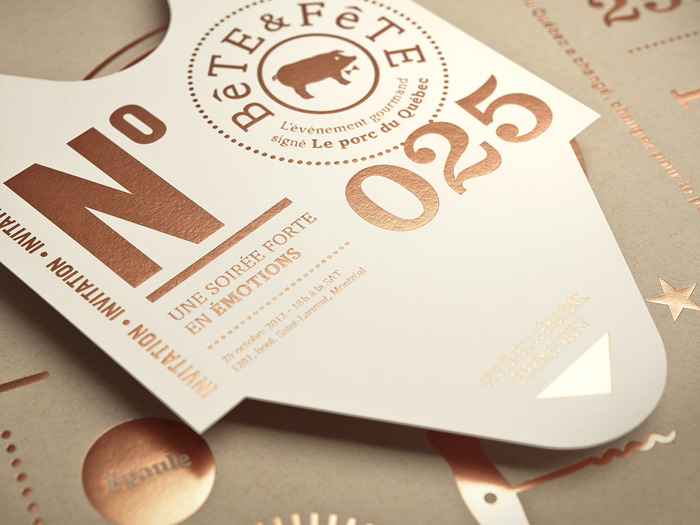
Schriftempfehlung
Da ich leider nicht vom Fach bind brauche ich einmal Rat von jemandem der
sich mit so etwas auskennt - nämlich von Euch.
Ich habe für meine Firma (Buchbinderei) ein Logo entworfen was genau meinen Vorstellungen
entspricht. Zu einem Logo gehören natürlich auch Briefbogen Visitenkarten etc.. Für diese benötige
ich unbedingt eine Schriftempfehlung, habe schon super viele ausprobiert aber so richtig stimmig
waren keine - ich hoffe auf Eure Unterstützung!!1
Ich habe den Eindruck Aria bzw. Aria Text könnte gut passen.
Aber auch eine »fließende« Sans wie Mr Eves halte ich für formal adäquat.
Zu Deinem Logoentwurf könnten eine ganze Reihe von Schriften passen, sowohl Serifenschriften als auch Serifenlose. Das hängt so ein bisschen davon ab, wie Du Deine Buchbinderei positionieren möchtest. Eher traditionell ausgerichtet könnte eine klassisch anmutende Antiqua wie die Mercury passen, zeitlos bis modern könnte eine zurückhaltende Serifenlose wie die TheSans eine Option sein.
Darf ich noch etwas zu Deinem Logoentwurf fragen? Mir gefällt die Idee wirklich gut und es sind formal sehr schöne Ansätze drin – aber eine fertige Reinzeichnung ist das noch nicht, oder? Ich frage, weil da noch einige Fehler in den Vektorpfaden stecken, die ich – wäre ich an Deine Stelle – unbedingt beheben würde, damit der Entwurf so richtig glänzen kann. Und dann fällt mir auf, dass Deine Datei mit »B&co« benannt ist. Ich lese aber: &BB@ oder &Bßo. Wenn die korrekte Reihenfolge der Buchstaben für Dich nicht relevant ist, dann passt es ja so. Andernfalls könntest Du da vielleicht noch einmal ansetzen. Das aber nur nebenbei bemerkt, ich möchte Dir mit meinen Anmerkungen nicht zu nahe treten – aber vielleicht helfen sie Dir ja ein bisschen weiter. :-)
Die Reihenfolge stimmt schon wenn man der Linie folgt ...
Ein paar stellen sollte man aber wirklich noch ausbeulen.
Bei einer Serif würde ich mal gucken welche einen ähnlichen Strichkontrast wie dein Logo hat – der ist ja nicht so riesig bzw. sind die Haarlinien nicht sehr fein. Die Aria Pro fände ich schon zu grazil – die Text passt besser.
Vielleicht gibt es auch eine schöne runde Slab oder eine moderne Clarendon-Interpretation die passen würde, mir fällt spontan allerdings nichts ein ...
Die Reihenfolge stimmt schon wenn man der Linie folgt ...
Ja, in Ordnung, das stimmt natürlich. Aber: Das hat sich mir bei der Betrachtung nicht direkt erschlossen. Ich habe die Zeichen von links nach rechts gelesen.
die ARIA finde ich nicht so optimal aber ohne zu wissen wie du dich sehen möchtest ist es schwer was zu sagen.
ich könnten mir auch (gerade zu dem klassischen logo) was robustes serifenloses oder wie schnitzel schon vorschlug, clarendon-artiges vorstellen.
das logo ist aber ganz schön verbeult, das müsste man eigentlich fast neu zeichnen. es sieht so aus wie gescannt und automatisch vektoriesiert.
die ARIA finde ich nicht so optimal …
Kannst Du das auch begründen? Ich fände wieder Clarendon zu derb für solch ein klassisch-barockes Gebilde.  ;-):hammer:
Vielleicht trifft man sich ja in der Mitte:
Wieder je nach Einsatz/Schriftgröße die Display- und Textvariante:
Und noch ein Schmuckstück:
Ich lese aber: &BB@ oder &Bßo.
… Ich habe die Zeichen von links nach rechts gelesen.
Ging mir so ähnlich, habe aber &BCo gelesen. Ist aber nicht so wild, wenn das Rätsel im Schriftzug aufgelöst wird. Es müsste meiner Ansicht nach möglich sein, einen Entwurf zu machen wobei sich die Reihenfolge auf Anhieb erschließt. Nicht jeder ist bereit oder kommt auf die Idee die Linie zu folgen. Es gibt aber Schlimmeres:
:–)
habe keine zeit für ausführliche texte.
mit formkontrast erreicht man manchmal mehr als mit harmonie.
wäre es mein job würde ich definitiv zwei unterschiedliche schriften einsetzen.
vielleicht so eine optik.
mit formkontrast erreicht man manchmal mehr als mit harmonie.
Wäre es mein Job, würde ich das als zusätzliche Variante vorschlagen. Dann aber keine breitlaufenden Serifen-Versalien sondern eher etwas Serifenloses in Richtung Univers, Flama oder gar Avenir, evtl. sogar condensed. Wenn schon Kontrast, dann richtig.  ;-)
Hatte aufgrund des Eingangs-Posts ursprünglich so etwas vor Augen (siehe Abb.). Erstmal abgesehen davon, ob etwas derart mondänes für einen Handwerksbetrieb zwangsläufig authentisch ist. Das kommt logischerweise auf die Qualität und das Leistungsspektrum an.
Das das Monogramm Schwindel erzeugt stimmt ein bisschen, aber besser kann ich halt nicht deswegen muss das erst einmal reichen.